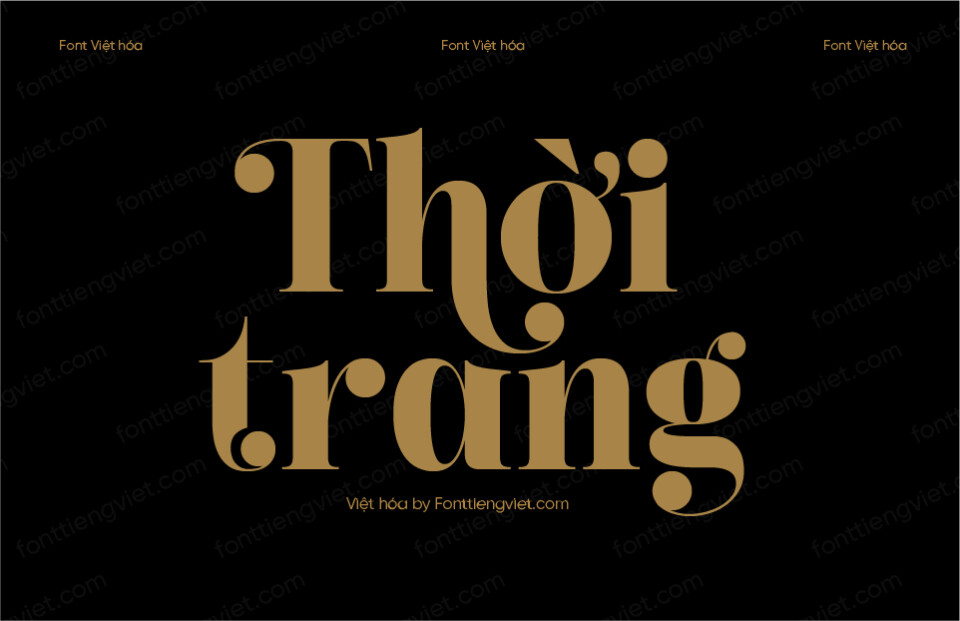
Font Việt hóa 1FTV VIP Ronagia
Font Việt hóa 1FTV VIP Ronagia – Sự Lựa Chọn Hoàn Hảo Cho Thiết Kế Sang Trọng
Trong thế giới sáng tạo, việc tìm kiếm một bộ Font Miễn Phí chất lượng cao luôn là ưu tiên hàng đầu của các nhà thiết kế. Font Việt hóa 1FTV VIP Ronagia nổi bật như một viên ngọc quý nhờ phong cách Serif hiện đại, tinh tế và đầy tính nghệ thuật. Đây là bộ phông chữ lý tưởng cho những ai đang tìm kiếm sự kết hợp giữa nét cổ điển truyền thống và hơi thở đương đại, giúp thông điệp truyền tải trở nên cuốn hút và chuyên nghiệp hơn bao giờ hết.
Khám phá đặc điểm nổi bật của Font Việt hóa 1FTV VIP Ronagia
Thiết kế đẳng cấp và tính ứng dụng cao
Font Việt hóa 1FTV VIP Ronagia sở hữu các đường nét thanh mảnh nhưng vô cùng chắc chắn. Điểm đặc biệt của bộ font này chính là sự cân bằng giữa các nét thanh và nét đậm, tạo nên một tổng thể hài hòa. Với bộ ký tự đầy đủ dấu tiếng Việt, người dùng có thể tự do sáng tạo mà không lo lỗi font hay thiếu ký tự. Đây là công cụ đắc lực cho các bài thuyết trình, dự án học đường hay các ấn phẩm truyền thông của nhà trường.
Phù hợp cho nhiều mục đích sáng tạo
Nhờ vẻ ngoài sang trọng, phông chữ này thường được ưu tiên sử dụng trong thiết kế logo, bìa sách, và các loại thiệp mời cao cấp. Đối với học sinh và sinh viên, việc áp dụng bộ font này vào các bài báo cáo sẽ giúp nâng tầm giá trị nội dung, thể hiện sự chỉn chu và gu thẩm mỹ tốt. Sự linh hoạt trong cách hiển thị giúp bộ chữ này hoạt động tốt trên cả định dạng in ấn lẫn kỹ thuật số.